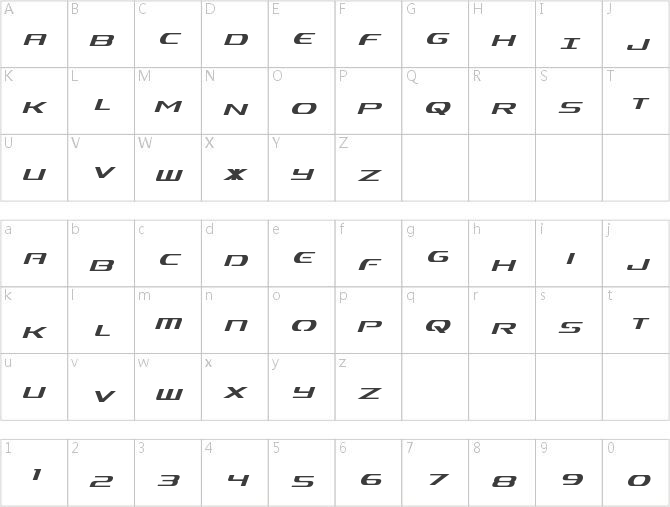
Alpha Men Condensed Italic
Alpha Men Condensed Italic介绍
Alpha Men Condensed Italic字体字库是一款让人赏心悦目、百看不厌的英文字体,适合各类广告和产品包装设计应用,字体大小0.02MB,格式为ttf字体,上传用户是雅迪,作者/版权方为未知